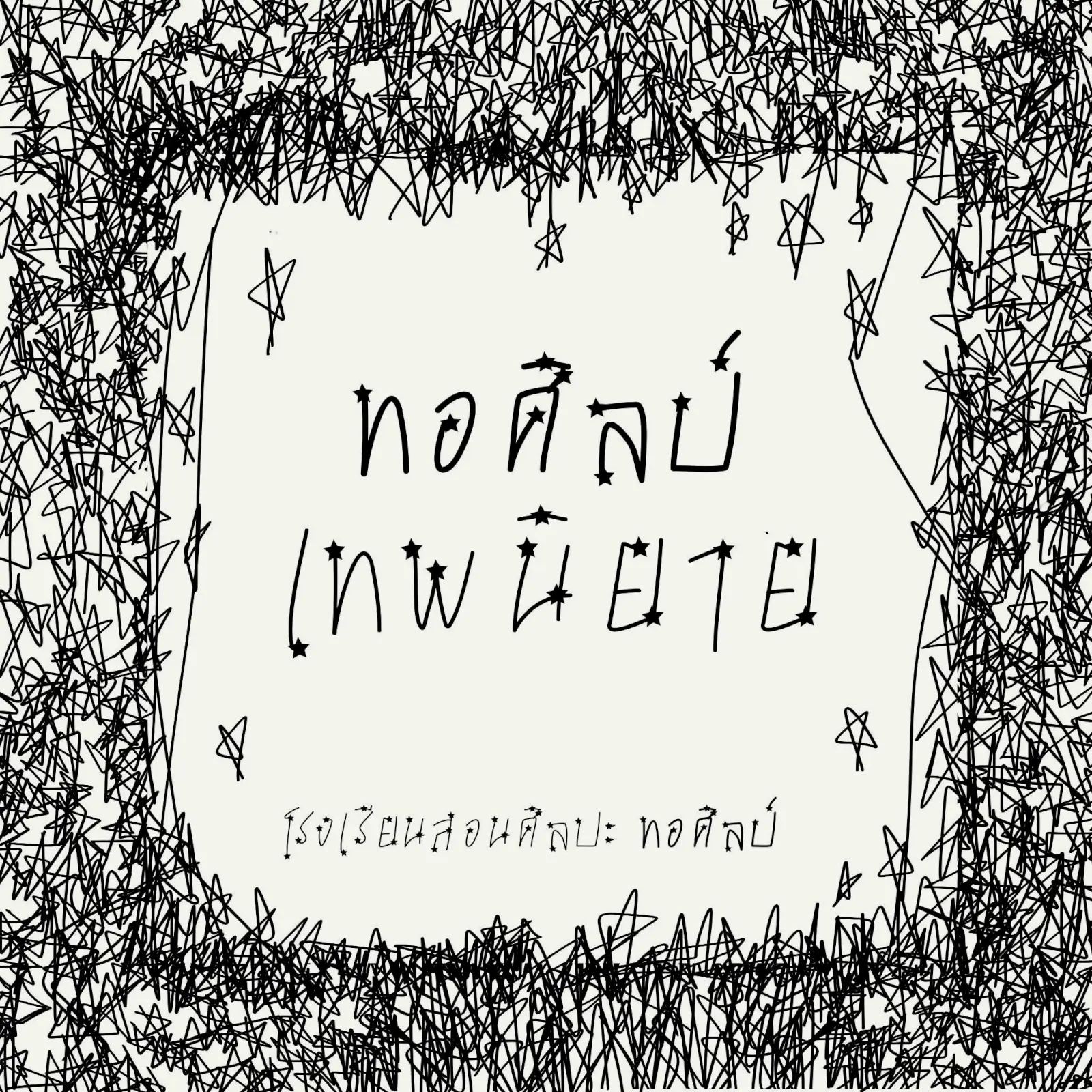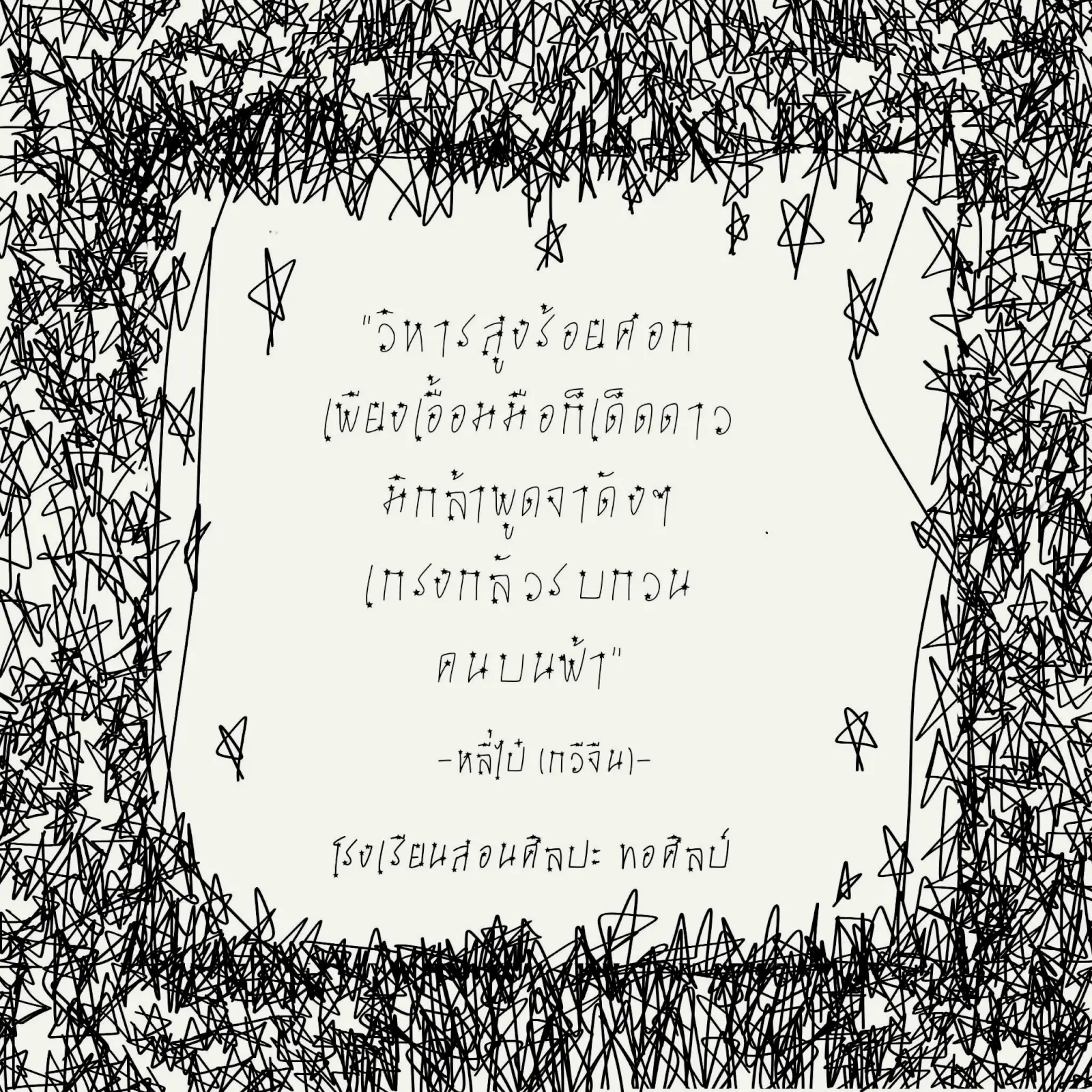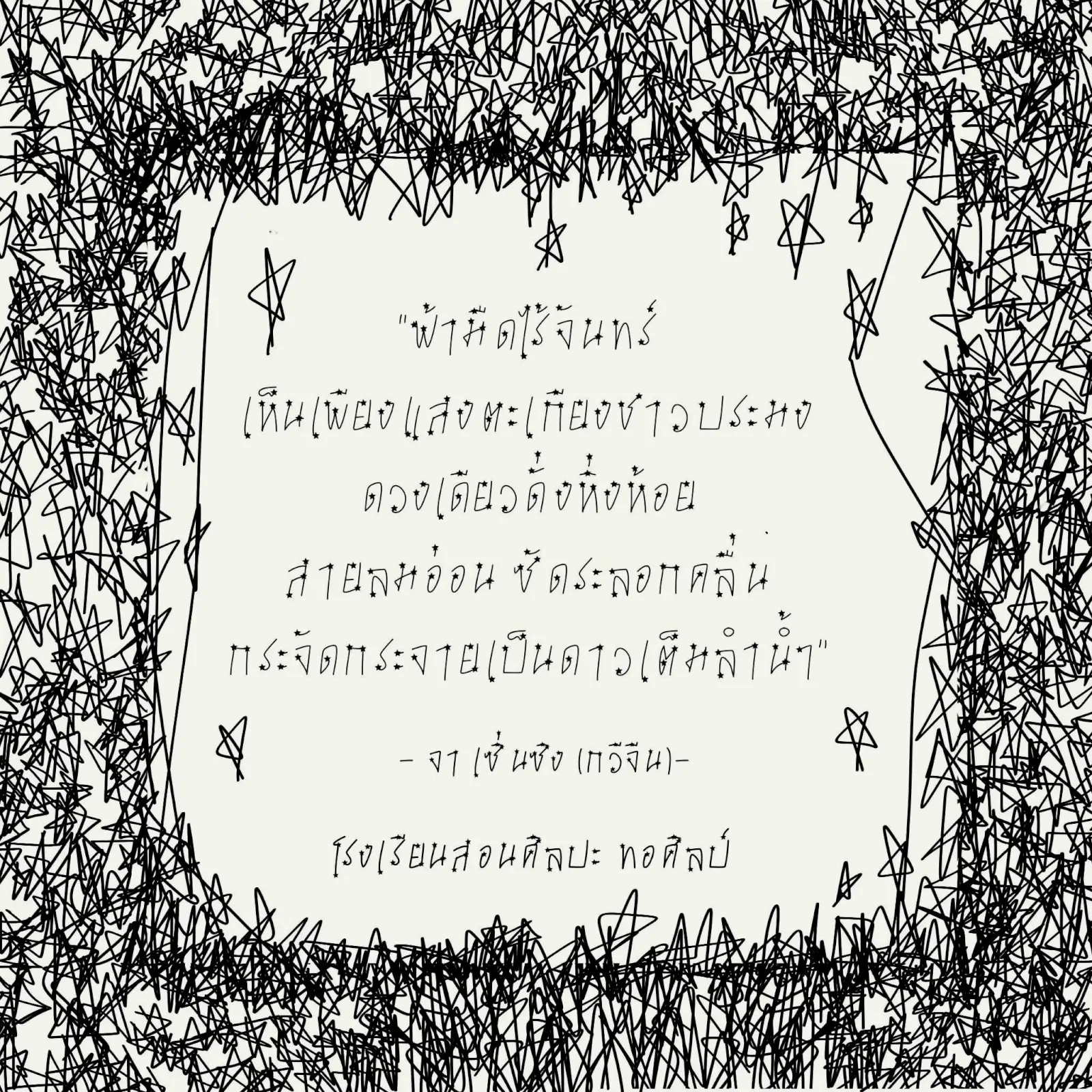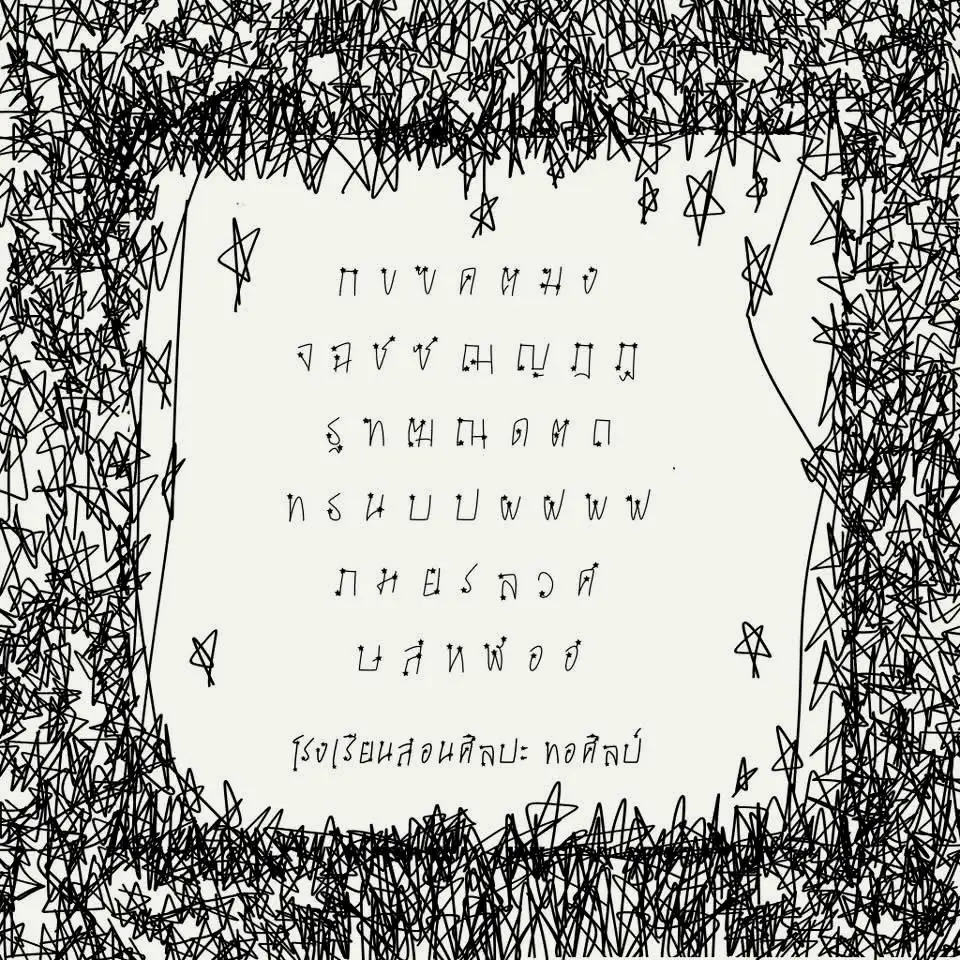
ฟอนต์ “ทอศิลป์ เทพนิยาย” – เป็นฟอนต์ลายมืออีกตัวนึง จัดวางแบบจังหวะขึ้นๆ ลงๆ เก๋ๆ เป็นธรรมชาติประดับดาวไว้ตามจุดต่างๆ ฟอนต์นี้เป็นการนำฟอนต์ “ทอศิลป์ คิดถึงเธอ” มาต่อยอด
ทำมาสองน้ำหนัก (ธรรมดา / บาง) แจกฟรี 1 น้ำหนัก (บาง)
ทอศิลป์ เทพนิยาย (Torsilp Thepniyai)